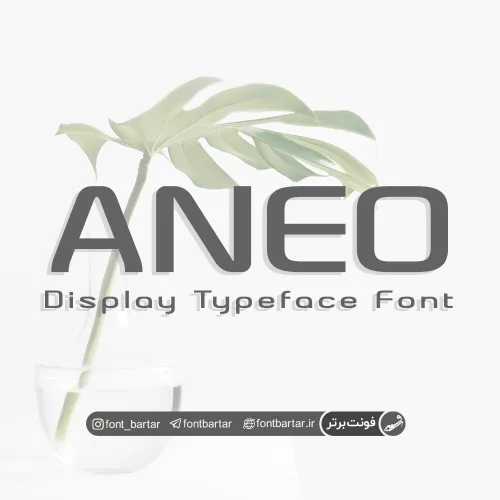
فونت انگلیسی ANEO
فونت Aneo در هشت وزن مختلف معمولی (Regular) ، ضخیم (Bold) ، مورب (Italic) ، ضخیم مورب (Bold Italic) و نسخه کشیده شده (عریض) همین چهار وزن طراحی شده است که می توان از آن ها در طراحی و گرافیک همچون طراحی صفحات وب ، طراحی بروشور ، کارت ویزیت ، تراکت ، بنر ، پوستر و … استفاده نمود.
- نام فونت : Aneo
- وزن : معمولی (Regular) ، ضخیم (Bold) ، مورب (Italic) ، ضخیم مورب (Bold Italic)
- به همراه نسخه عریض فونت
فونت انگلیسی ANEO مورد استفاده برای: